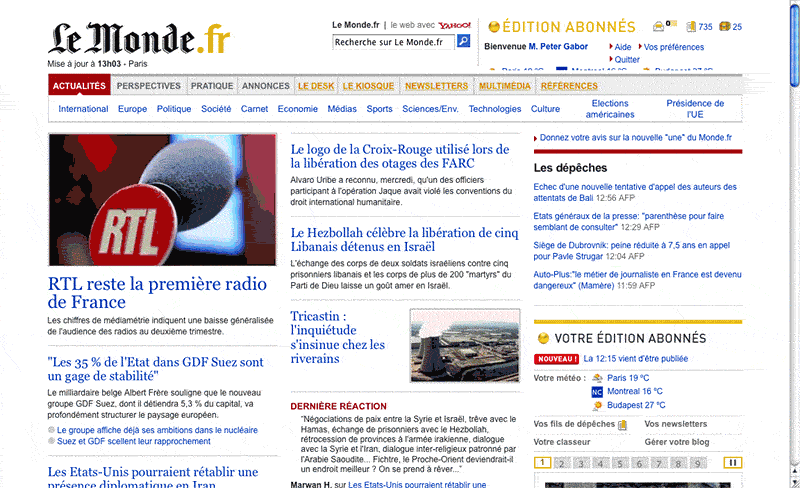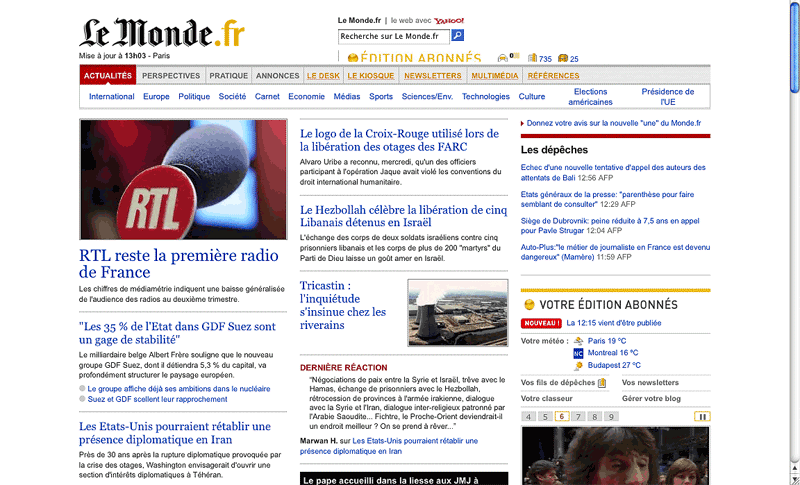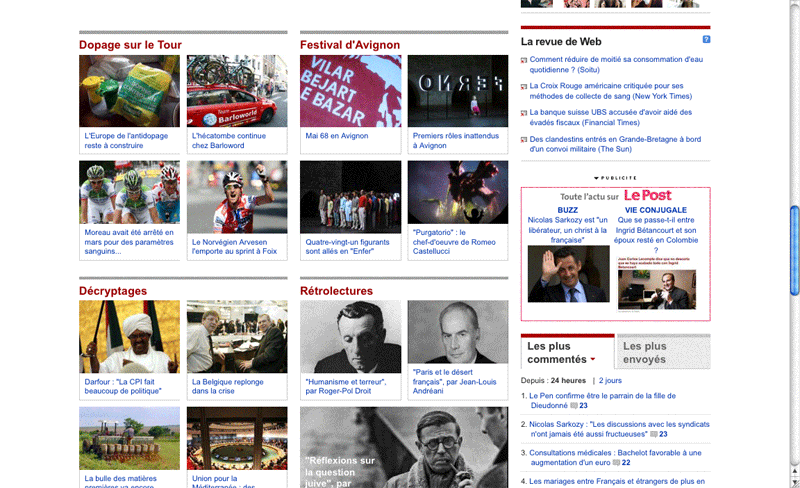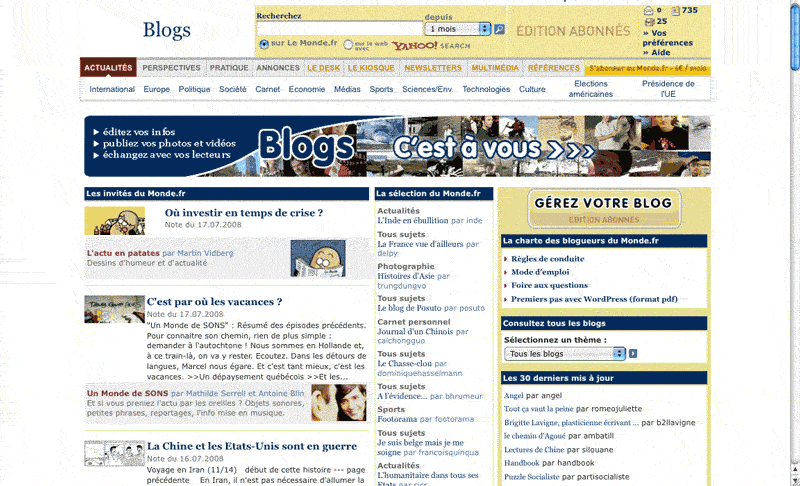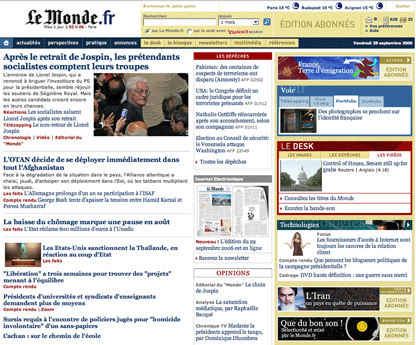
Le Monde.fr | typographie et mise en page à l’honneur | analyse
Voici quelques jours que la nouvelle maquette du Monde.fr est en ligne. Et l’on peut déjà tirer quelques conclusions de ce travail non dénué d’intérêt. L’évolution s’est faite en toute discrétion. Point d’annonces fracassantes ni de conférence de presse de la rédaction. Quelques frémissements, dans les pages internes, «on sentait que quelque chose bougeait», puis depuis cette semaine la Une s’est radicalement transformée.
Quid de cette évolution. Pour les qualités:
1) Plus éditoriale
Un sujet qui m’a préoccupé dès le démarrage de design et typo. Ai publié en octobre 2006 une étude comparative de la presse en ligne ici …   Voici (ci-dessous) à quoi ressemblait en 2006 la Une du Monde. Présence forte d’une grille sursignifiée par des cadres, des encarts et des filets. Au point que le contenu avait tendence à disparaître au profit des signifiants graphiques. Une maquette très «DSI» qui ne tenait pas trop compte du confort du lecteur bien incapable d’analyser les codes graphiques qui lui confère confort et lisibilité.
La nouvelle maquette bénéficie donc d’un effacement radical de cette charte surabondante pour laisser respirer et vivre le texte éditorial du journal on-line. Preuve en est que le blanc reprend le dessus et sa circulation rythme la lecture de la page d’accueil. Il n’y a plus de cadre, juste quelques filets rouges ou jaunes qui contrastent agréablement avec les titres et textes bleus.
Redonner aux titres et textes leur primauté. Un journal, en ligne ou Print c’est tout d’abord des articles. Puis quelques photos qui viennent illustrer tout en rythmant la mise en page. Il s’agit bien sûr d’une contrainte majeure… mais il ne faudrait surtout pas en conclure qu’il suffit de supprimer les cadres et les filets pour conférer «une forme éditoriale» à un Site d’Actus. Les variables sont nombreuses. Choix des caractères (Georgia pour les titres et Arial pour le texte courant), choix de la hiérarchie des corps et surtout, choix des interlignes et des filets très très fins en pointillés qui viennent juste signifier une subdivision indispensable à la lecture. Le résultat est nette et sans bavure. On n’est pas là pour s’amuser mais pour s’informer. Et Le Monde a enfin compris sans doute encore parmi les premiers, les ingrédients de cette lecture très spéciale. Il est à noter que la circulation des blancs est remarquablement bien réglée. On y reviendra.
l’ancienne maquette du Monde.fr.
2) Mieux hiérarchisée
Tout d’abord il faut signaler que le flux est sans cesse remis à jour à une cadence que j’ai rarement vu ailleurs. Preuve d’une fébrilité journalistique de chaque instant. La rédaction respecte bien le concept des 4-5 articles principaux qui «sautent aux yeux» du lecteur, mais l’ordonnancement et l’énumération de ces articles bouge très vite. Exemple du jour: l’I-Phone qui monte en titre principal à 17:00h alors que vers midi on faisait focus sur l’audience d’RTL. Ce flux est sans doute l’arme stratégique du Monde.fr car il engrange du fil RSS et des référencements constants. On peut aisément deviner que l’audience du portail va augmenter de façon substentielle.
3) Plus d’ergonomie
Une seule barre de navigation horizontale sans bric-à-broc 2.0, l’essentiel, les principales rubriques. On survole et à chaque onglet correspond une ligne de navigation «sensible» et non soulignée avec un focus qui varie lors du survol. Dès que je quitte cette ligne la parenthèse verticale se referme, je regagne de la place de lecture pour la suite. (Et la grande force de cette mise en page est d’avoir concentré dans la partie supérieure gauche les principaux titres de l’heure. Un seul titre en c.24 et les autres en c.17. Quant aux textes, composés en c.10-11. ils bénéficient d’un interlignage très confortable.) Dans la zone Livres et Culture, dans un espace où le besoin d’images se fait encore plus sentir que dans les actus, chaque photographie se joue en rollover par un texte blanc sur fond rouge qui vient préciser le contenu de l’article. Vous cliquez et direct to the article, comme avant. De fait la typographie interne du portail n’a pas encore été modifiée. Vous y retrouvez l’ancienne maquette et charte graphique.
Pour les défauts:
1) Une mise en page un peu ennuyeuse, voire monotone
Elle tient essentiellement à la grille verticale en trois colonnes pas tout à fait égales*. La tiercéité symétrique de cette mise en page nous enferme dans un non-rythme graphique (voire musicale) qu’il eut suffit pour rompre, d’intercaler une colonne de texte ou tout simplement une marge plus grande entre les deux premières colonnes et la dernière. Et cela m’amène à me et vous poser une question, pourquoi diable continue-t-on à laisser des marges latérales aussi importantes sur la quasi totalité des portails de presse?
J’ai bien une idée qui concerne l’ergonomie de lecture et la possibilité d’agrandir les corps, la peur d’éparpiller le regard du lecteur, et peut-être une difficulté supplémentaire pour implémenter les flux d’infos qui arrivent en php etc.
Cela dit, regardez-ci-dessous la home du New York Times et vous comprendrez qu’une grille en quatre colonnes (qui se termine par une grille sur six colonnes) est plus vivante et donc plus riche d’expérience de lecteur.
Le secret de tout rythme est l’assymétrie qui transgresse le tempo. Et le tempo graphique est commandé en premier lieu par les colonnes puis les blancs tournants et enfin par la hiérarchisation typographique. La nouvelle maquette du Monde.fr ne souffrirait-elle que d’une chose: un manque d’accidents graphiques (voulus et donc signifiants). Il s’agit d’une maquette très élégante, très agréable et très «rigoureuse», qui ne souffre que d’un manque de personnalité *trademark Le Monde*.
2) Une charte Graphique très benchmarqué entre El País.com, Google Actus le New York Times et le Guardian
Ce serait sans doute la plus mauvaise critique à faire au Monde, que de regarder autour, les sites qui fonctionnent bien. Google, en premier (je crois) avait inventé un style de News sans images, une sorte d’agrégateur d’Actus personnalisable à souhait. (c’est d’ailleurs sans doute le devenir d’un portail comme le Monde). Deuxième grande étape vers *Son Journal à Soi* et déjà en œuvre sur de nombreux portails (BBC ).